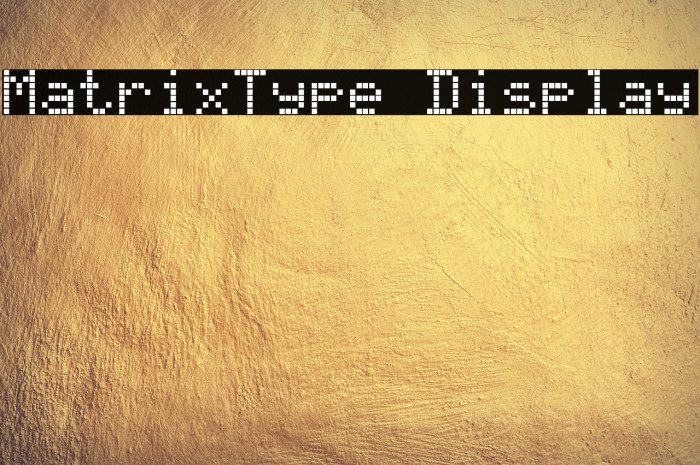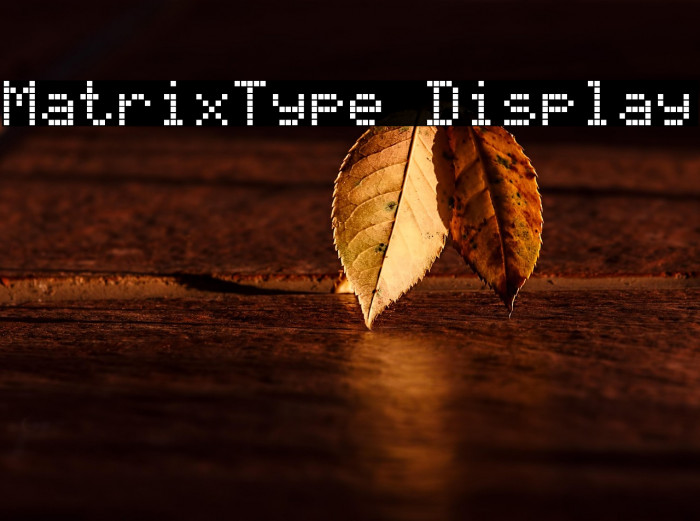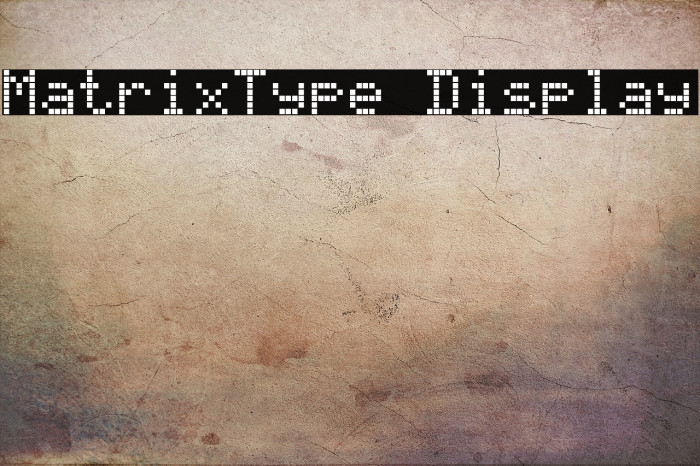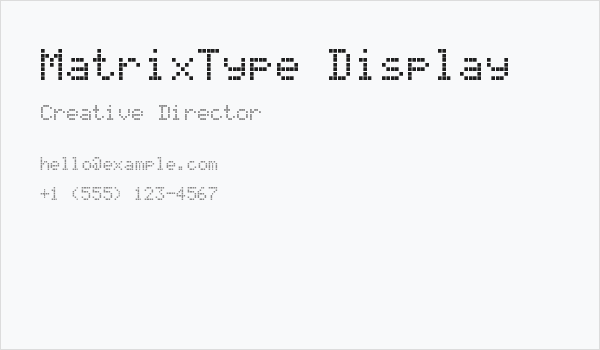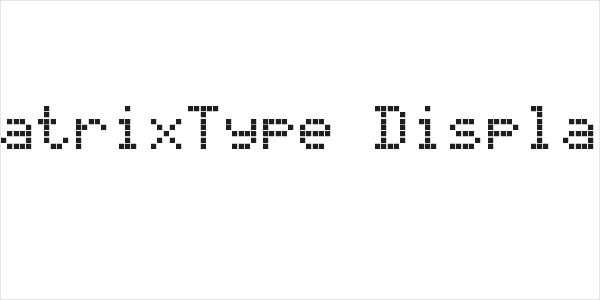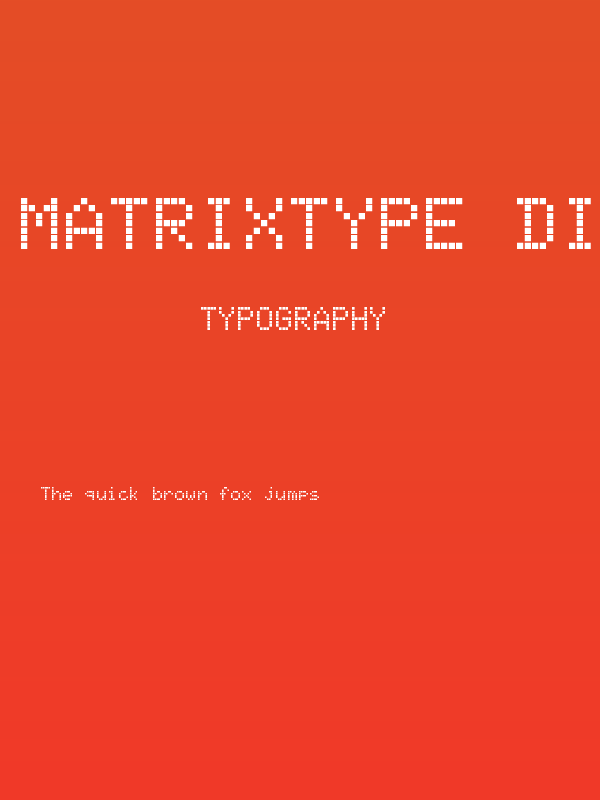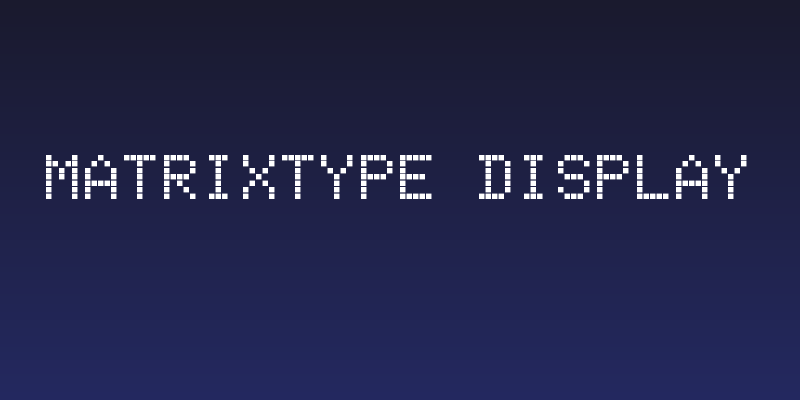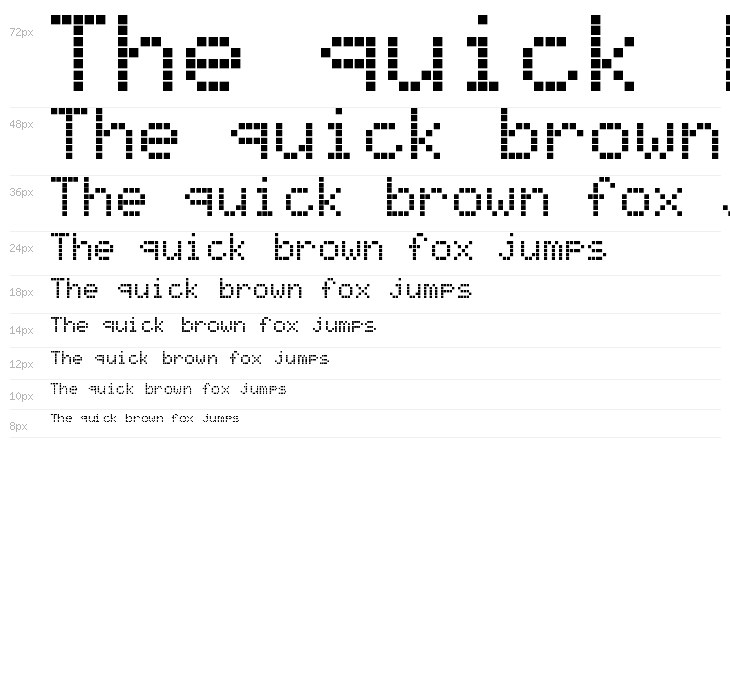
MatrixType Display Font
| Gesamtstil | Retro, Digital |
| Anwendungsfall | Logos, Headlines, Digital displays |
| Vorgeschlagene Projekte | Ideal for retro video game graphics, digital art projects, tech-themed posters, and any design requiring a nostalgic digital aesthetic. |